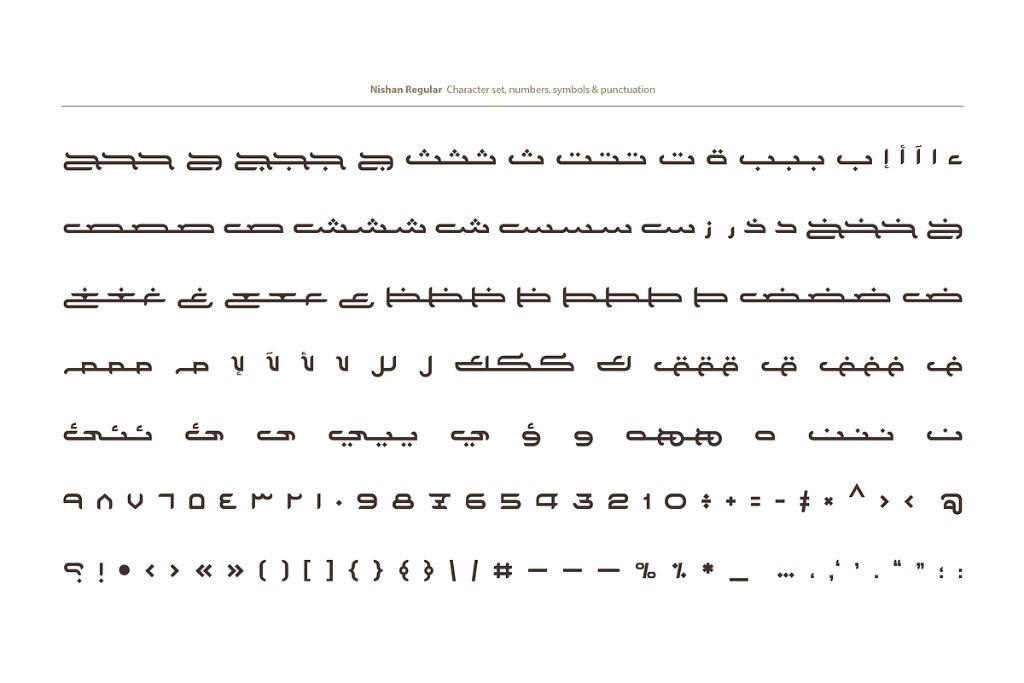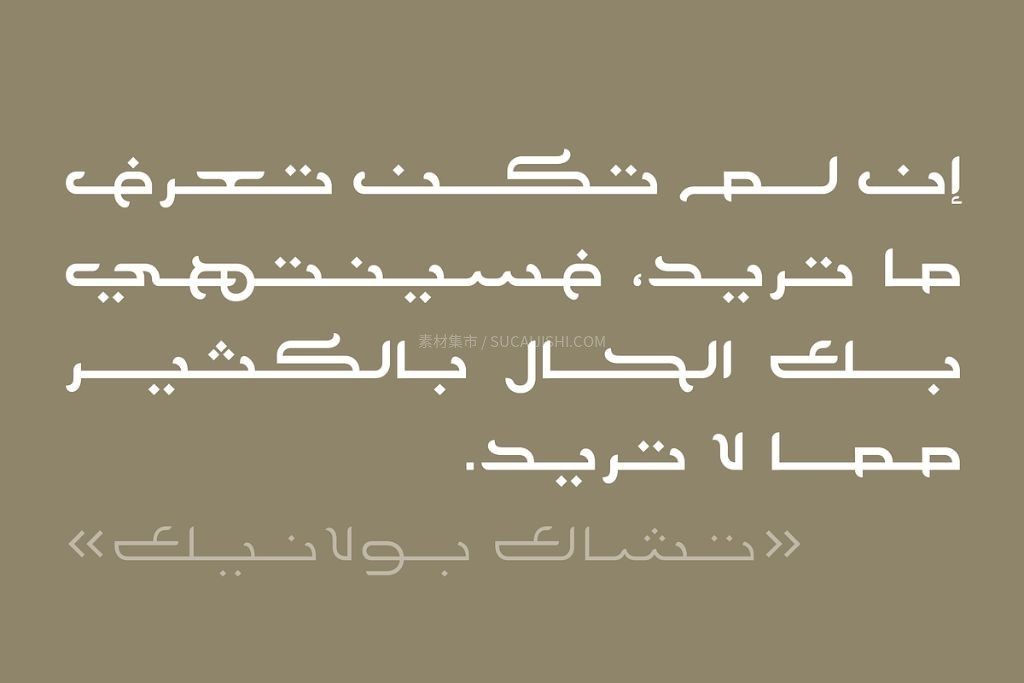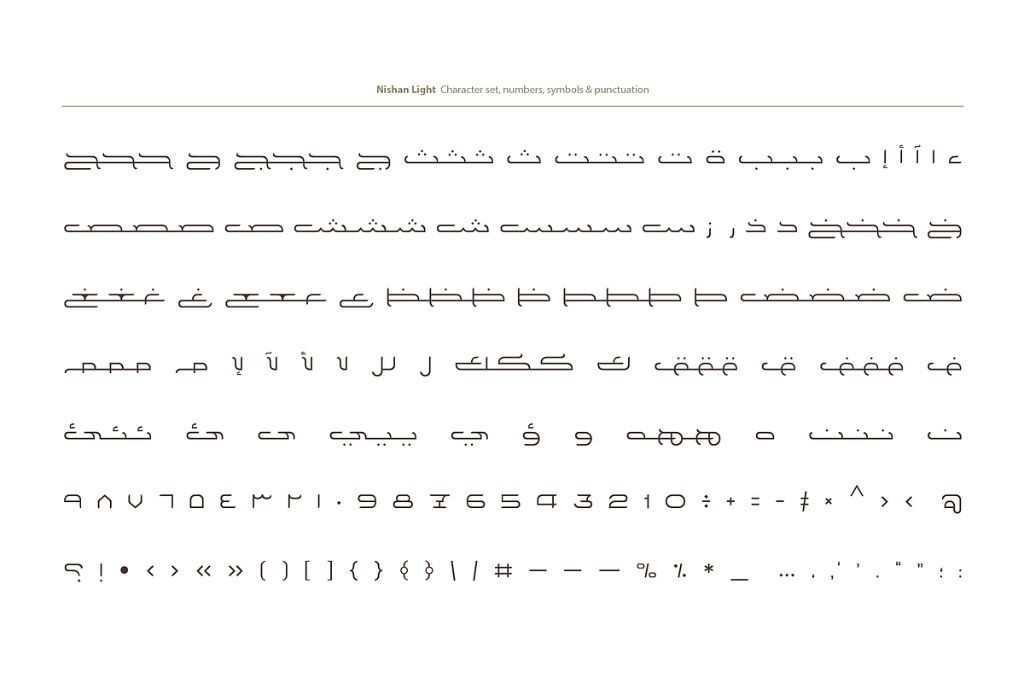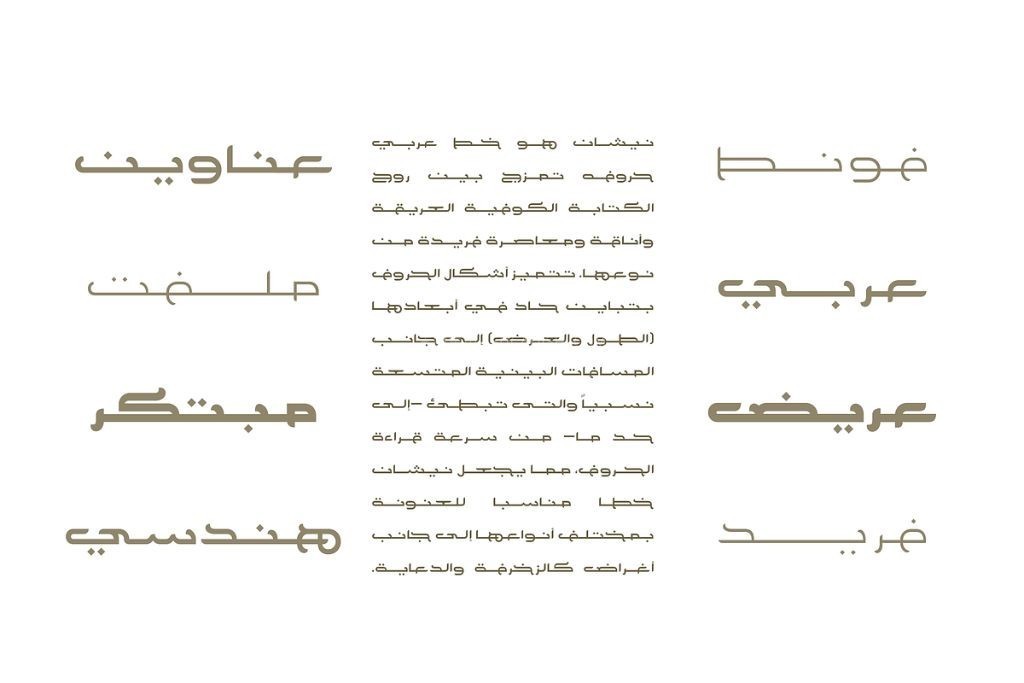
Nishan 阿拉伯语创意书法字体
Nishan 是一款将古典美学与现代设计完美融合的独特字体。该字体的核心特色在于字母尺寸(长度与宽度)强烈的视觉对比,结合较宽的字间距,营造出一种疏朗、通透的艺术感。虽然这种布局对长文本阅读有一定挑战,但其极佳的视觉张力使其成为创意排版、艺术海报及品牌设计的理想之选。